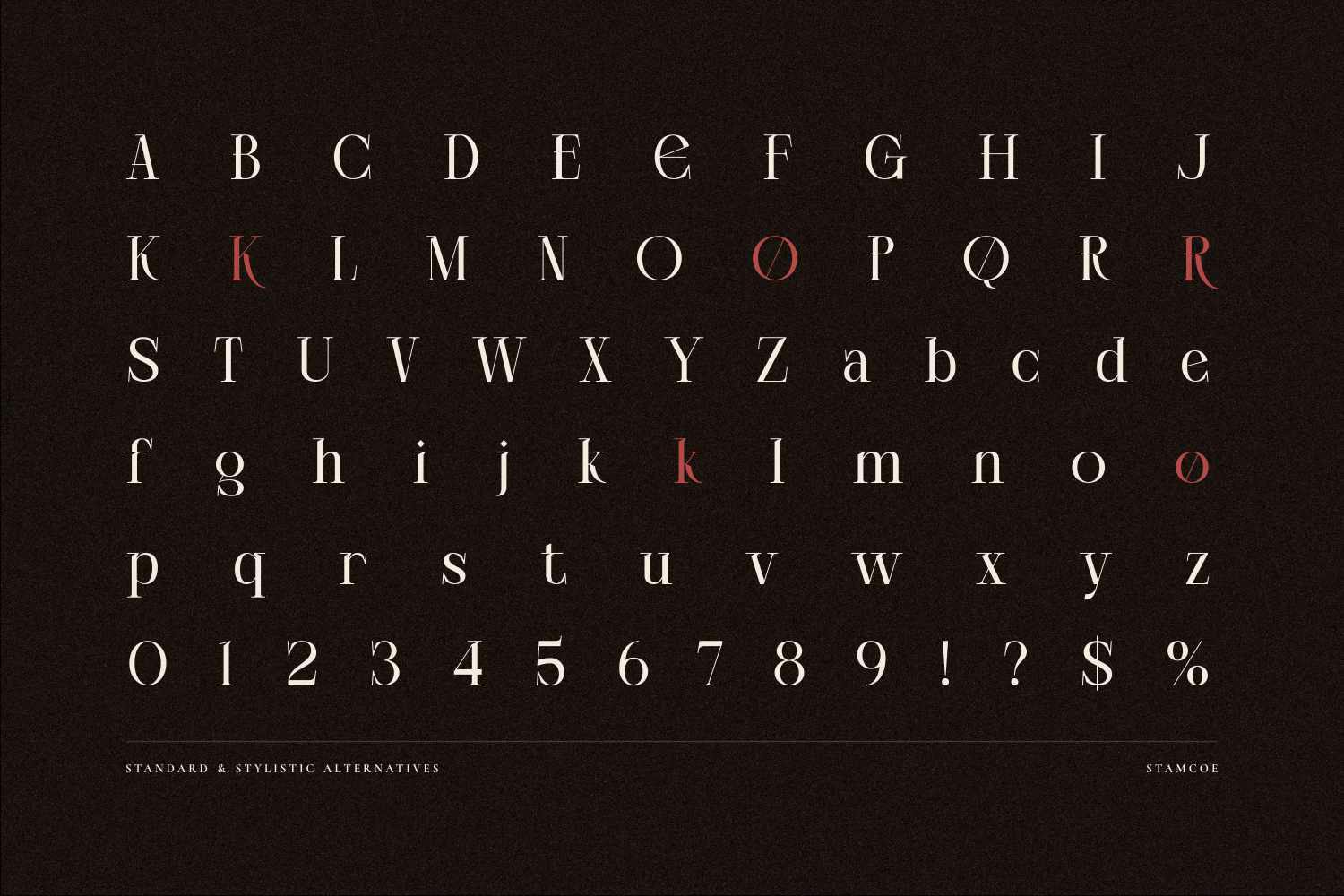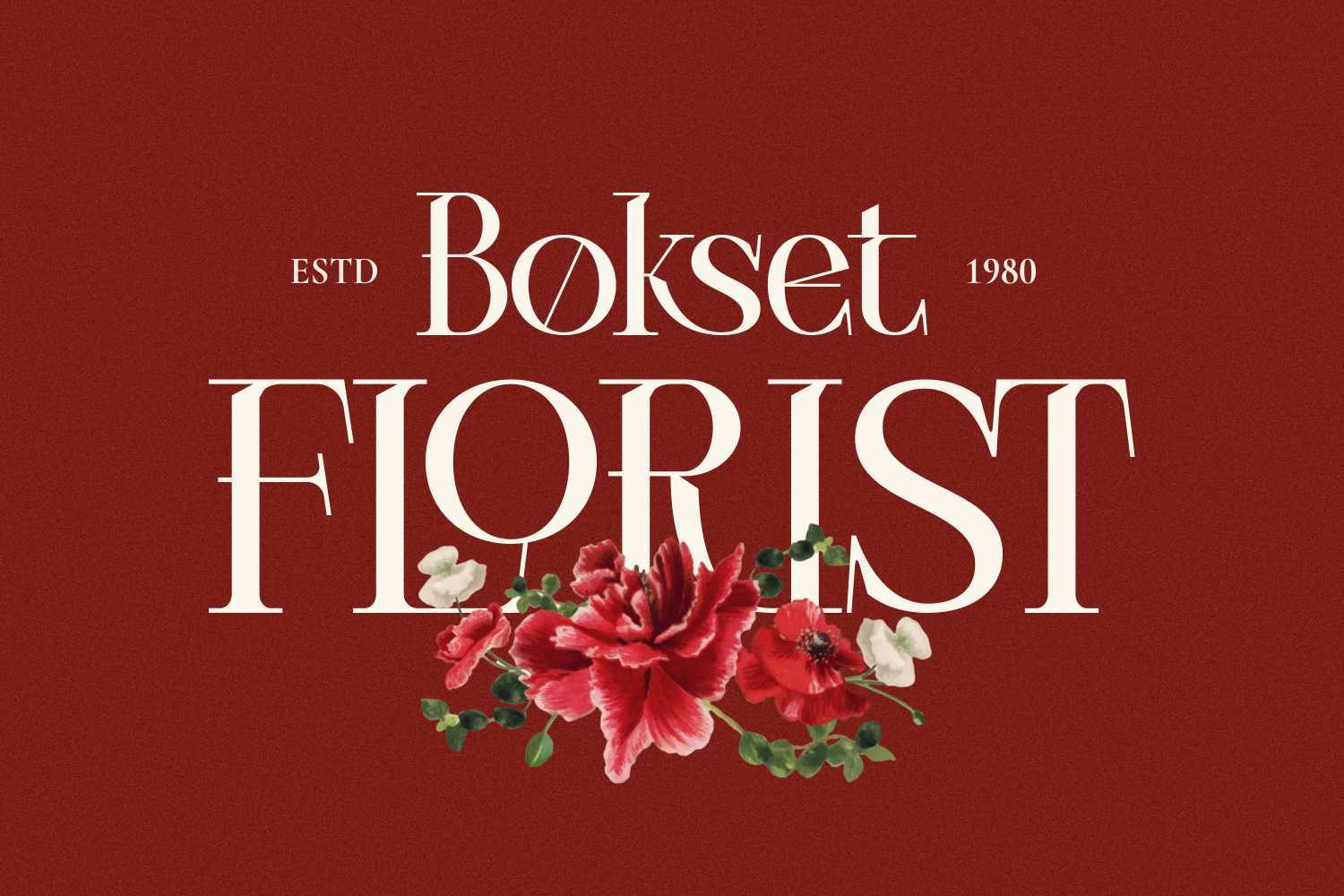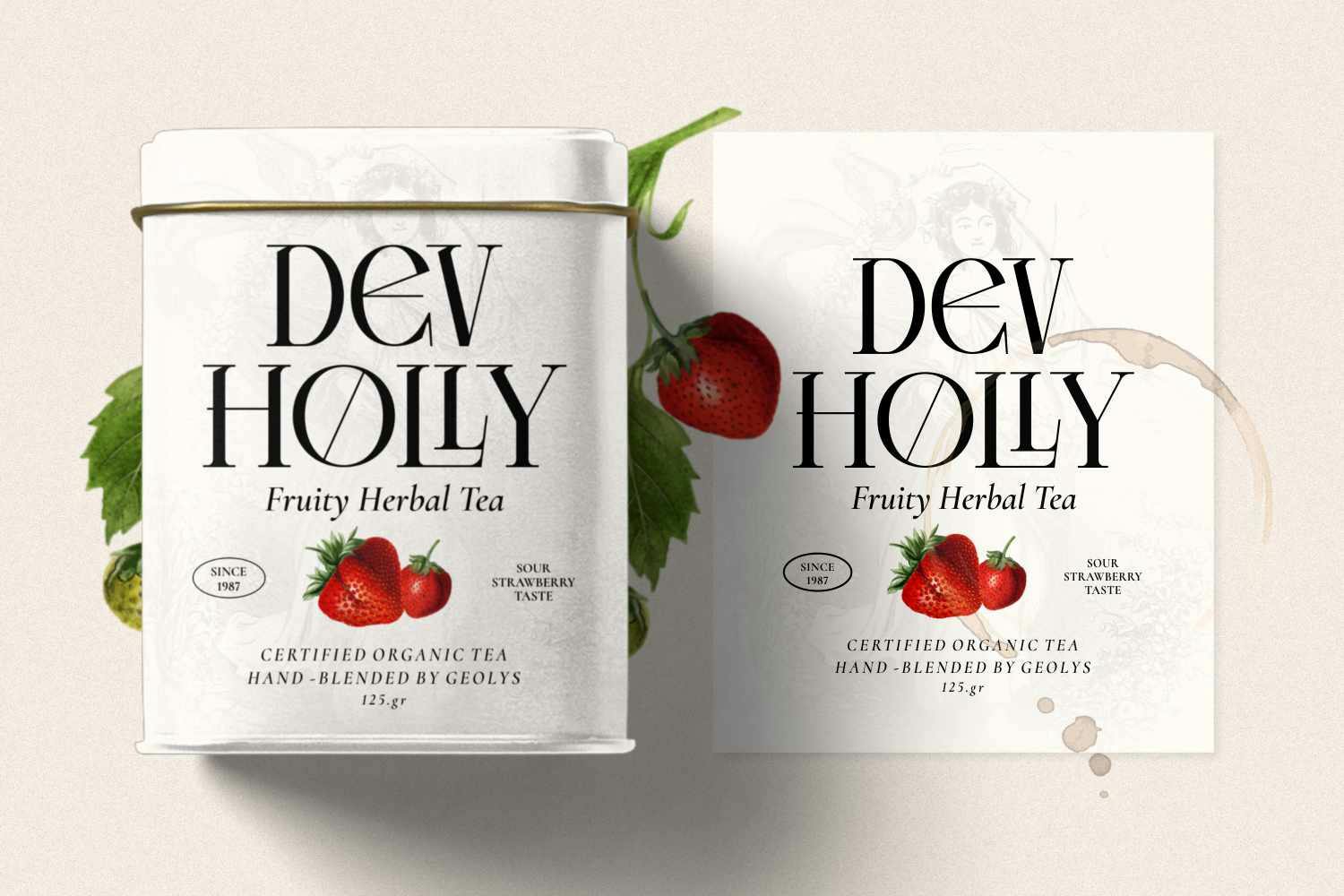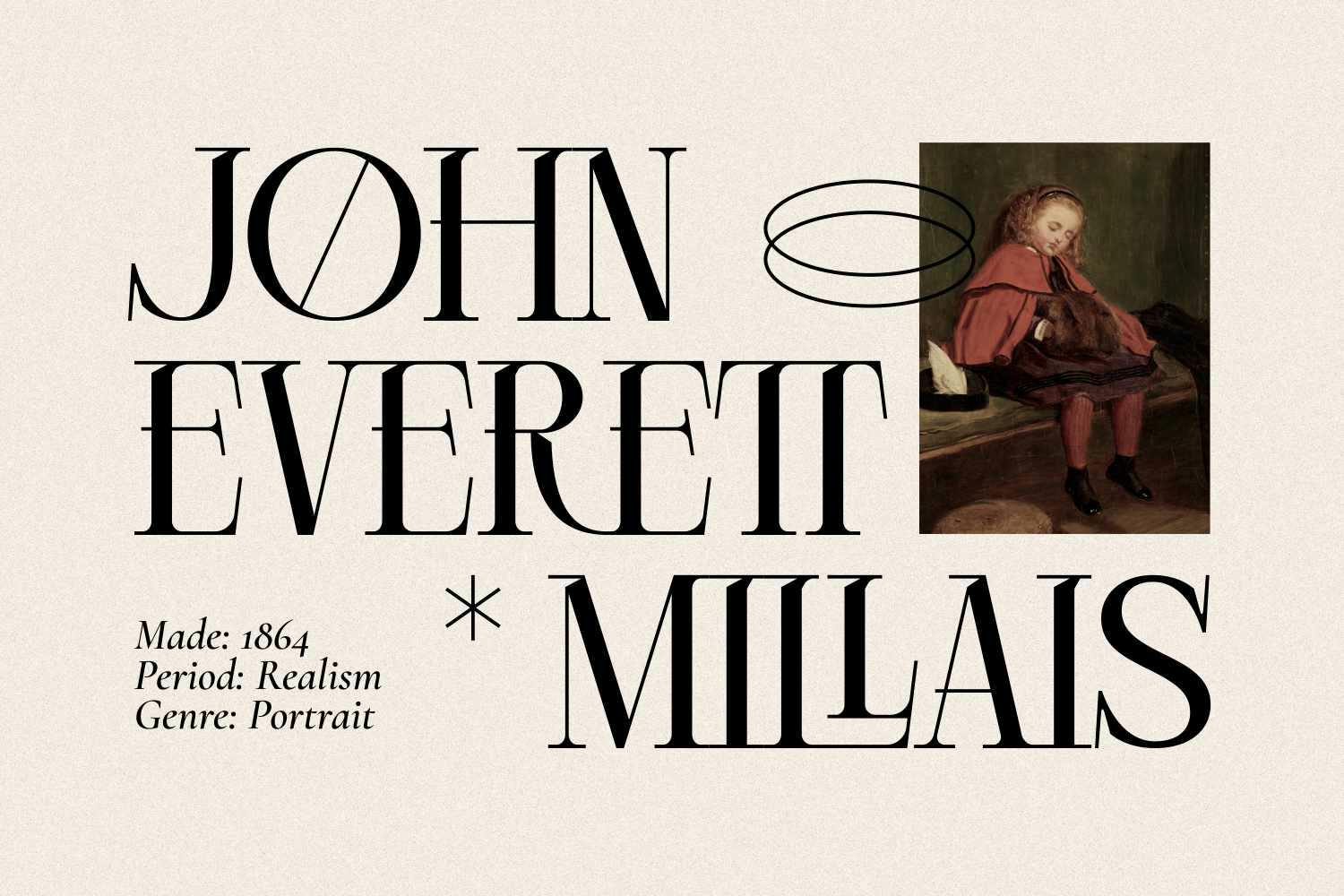
محصول فونت استامکو برای بسیاری از پروژههای شما مانند لوگو و برندینگ، عکاسی، دعوتنامهها، واترمارکها، تبلیغات، طراحی محصولات، لوازم التحریر، طراحیهای عروسی، برچسبها، بستهبندی محصولات، رویدادهای ویژه و موارد دیگر بسیار مناسب است.